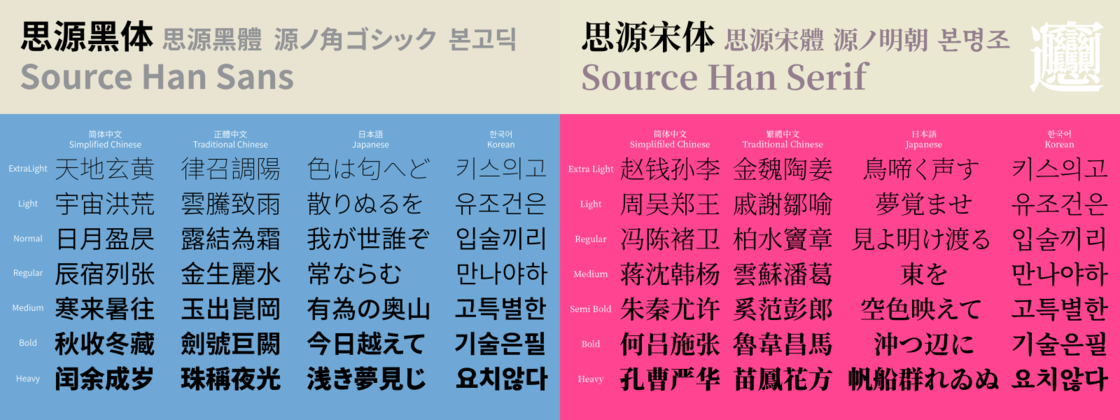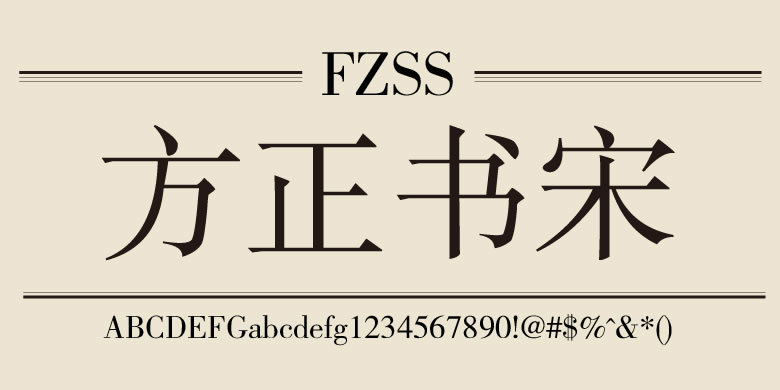
字体使用个人参考指南
文字作为我们交流的主要载体,手机、电脑、文书合同等各个方面。字体的侵权跟大多数版权内容一样,它的判定为两种:
1、商用
2、非商用
但是我们对字体版权的意识,往往不如其他内容版权那么关心,比如图片、影视、商标等等。因为文字过于常见,所以不小心就是一踩一个坑。
相比普通群体,更应该注意的是那些电商、小型公司、中小型公司以及大部分的创业群体。电商产品的宣传封面所使用的字体,很多时候为了节省成本,不会聘请专业美工,而那些接单的新手相对意识比较薄弱或者自己制作,就比较容易导致侵权。
给大家分享一个电商海报字体的案例,看下图。
这位从事电商行业的朋友,使用了未经方正授权的 “ 微软雅黑 ” 。
在图中也可以清楚看出,一旦侵权,那作为侵权方就尤为被动,一点话语权都没有。即便你有什么任何理由,也掩盖不了未经授权的事实。而在公司以及创业者方面,更多的是合同内容所使用的字体。这也可能是下文中的电商大站会自建或外购字体为其所用的一个最重要的原因吧。
在这里还要说明一点,电脑等等自带的字体不代表你有使用权,那是字体方授权给电脑系统使用,而不是给你商用的。拟定合同或者相关协议的时候,使用电脑自带文体正常不过的事情,但也要区分字体。
再看一个相关例子:
2019年,成都某公司的实习生,在拟定合同以及在宣传海报上使用了“微软雅黑”。并且这份宣传单被印刷了5000万张,发放到了全国各地。最后这家公司被索赔2860万,裁掉了8位主管和42位员工,公司一度濒临倒闭。这是多么痛的领悟。
这些都是真实事件,在网上动动手指都可以查到。而且你只要在网上搜索相关关键字,会发现这种案例比比皆是。
2011年,方正也因为字体侵权起诉飘柔。
2016年,某电商平台店主集体收到了侵权的律师函。
所以不管是大商家还是小商家、大公司还是小公司,对于字体的使用要保持一个严谨的态度,别一失足成千古恨。字虽小,但麻烦很大。
除了那些被我们熟知的宋体、黑体之外,还进行了系列梳理。
一、方正4款:方正黑体、方正书宋、方正仿宋、方正楷体。
二、思源2款:思源宋体、思源黑体。
三、王漢宗自由字型48款,内容太多,以图代字。
四、文泉驿字体4款:文泉驿等宽微米黑、文泉驿等宽正黑、 文泉驿微米黑、文泉驿正黑。
五、站酷字体4款:站酷酷黑体、站酷意大利体、站酷快乐体、站酷高端黑体
其中大多都是黑体、宋体的改变延伸,但不是代表所有带有 “ 黑 ” 或者 “ 宋 ” 字样的字体都是免费,微软雅黑就是例子。
字体有前缀或者参杂其他字样的,其实都应该引起注意,但也有解决办法,现在网络上有很多字体版权的查询网站,只要把你想用的字体输入,便可以查询是否为商用。
微软雅黑与北大方正
推动中文字体发展的居然是美国微软公司,为了让中文字体更好看,微软公司高价委托第三方字体设计公司开发了微软雅黑字体,每个汉字的造价成本在100美元左右,而我们有2万多个汉字。中文字体非常少,而优秀的中文字体更是凤毛麟角,我们常见的中文字体主要是宋体和黑体,其他很少见,因此,时间长了很容易出现审美疲劳,字体设计这一块做得最好的应该就是英文和日文了,其实我们是有能力开发优秀的中文字体的,但为什么就很少见呢?
2006年,微软的Windows Vista操作系统发布,为了让中文字体可以更清晰地显示,微软公司委托中国北大方正电子设计了一款全面支持ClearType技术的字体,就是现在人人熟知的微软雅黑字体,现在新的微软操作系统和程序默认的字体都是微软雅黑,另外还有网页上的字体基本上都是采用微软雅黑。
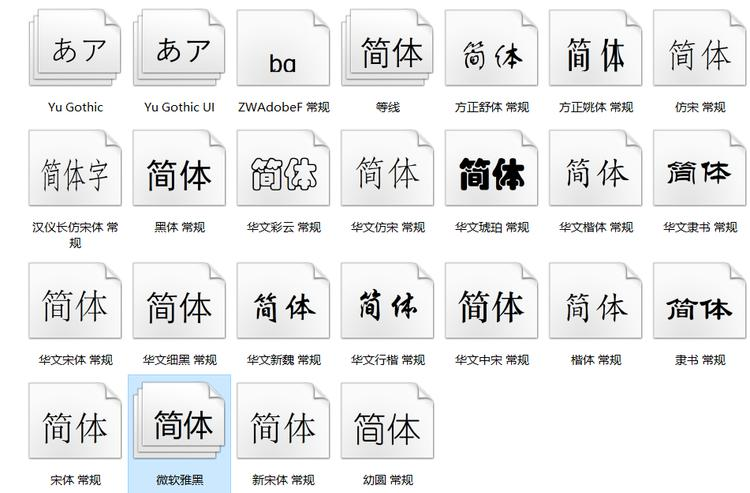
微软雅黑字体其实并不是完全免费的,微软雅黑的版权分为两个部分,一个是以个人使用为目的的Windows系统的内嵌使用、屏幕输出和打印,另一个是以商业发布为目的的微软雅黑版权,由北大方正保留,因此,用于商业目标的可能面临字体侵权,市面也有新闻报道过,上文也有引用,还是有不少公司使用了微软雅黑而被北大方正巨额索赔。也就是说:微软雅黑居然是北大方正开发的,一个字100美元卖给了美国微软公司。
中文字体设计,几十年了一直在原地踏步,其实说到底还是利益问题,国外有很多设计师就喜欢免费分享自己的作品,而国内设计师还没有这么高的境界。虽然字体设计还有一定差距,但这不是实力的问题,而是我们愿不愿意分享的问题,相信以后会有越来越多的优秀字体出现。
注意:没有醒目提示的,都要斟酌,不排除某些人就是靠此种手段谋利的可能,商用或者免费可能都会写在附文里,字小还多,很多朋友都不会认真阅读。如果真的喜欢一些需要付费的字体,就破点小财消大灾吧。说完上面的商用字体,下面就开始使用友好的字体介绍之旅吧。
字体侵权一说
本节摘自于张宇铭先生的总结。字体是受法律保护的,大家在使用时不能存有侥幸心理,来看看字体侵权问题案例。
影视作品侵权案例
2012 年的《九层妖塔》,仅使用了未授权字体中的 7 个字,就被索赔 51 万元。
电商广告侵权案例
电商也是字体侵权的重灾区,网络广告、海报、宣传语、商品包装、宣传视频、企业网站等。
如何界定一个字体的版权是否属于侵权?
所谓版权是专属知识产权,如果是大众的、通行的字体的使用不涉及版权争议,比如宋体,楷体,颜体……如果是自创体,不是大众使用与通用的,并在其中承赋了创造含量,或根据通用字体而编缉出版的字贴、字模等,并申报了相应的保护则具有了版权,如果被他人盗用则会涉及版权纠纷。
根据《中华人民共和国著作权法》的规定,作品在以下一些情况可以不经授权也不需要付费即可使用。为个人学习、研究或者欣赏;在介绍、评论中适当引用;为学校课堂教学或者科学研究;新闻报道;国家机关为执行公务合理范围内使用;公益陈列、保存、表演;转换成少数民族语文和盲文。对于字体内容,个人普通使用以及公益使用都应该采取自动获得授权方式。只要以合法手段取得已经发表的字体应用于以上领域,不需要获得授权,也不需要付费。
商业使用,不管是新设计字体还是作为文化遗产传承下来的宋体、仿宋、楷体、黑体等字体,都需要获得授权。新设计字体采取何种授权方式由著作权人决定。而宋体、仿宋体、楷体、黑体等传统字体作为全民族共有的非物质文化遗产,则应由国家相关机构代为管理。从理论上讲,如果取得收益应该返回给权利所有人,也可以变通为开放式授权,全民免费使用。但这仅应针对中国人,如外国企业作为商业使用,则需要取得正式授权。
字体产品的版权保护期。字体产品的版权保护也需要设置期限,应针对传统字体与新字体分别设置:传统字体按照《非物质文化遗产法》实行永久版权。新字体则适用《著作权法》和《计算机软件保护条例》,保护期为 50 年,期满转为公共资源,以鼓励不断创新。
依据《中华人民共和国著作权法》第三条,著作权包括文学、艺术和自然科学、社会科学、工程技术等版权,字体属于计算机字体库内容,平时在使用某系统时已经包含了其计算机字体库。
界定一个字体的版权:
1.确定字体是否收费,可通过拨打字体厂商电话,网络查询等。
2.确定是否用于商用,所有字体如果用于个人作品展示、参加各类非商业性比赛等非商业活动,字体厂商不追究版权问题。
3.确定是否变形,文字变形是否超过 50%,上述 50% 是法律法规界定,十分模糊,通常设计中字体变形或者造字,请注意变化尽量最大化。
商业使用的界定:商业使用包括以直接营利或者间接营利为目的,将字体作为视觉设计要素,进行复制、发行、展览、放映、信息网络传播、广播等使用字体的行为,比如,在企业宣传、广告设计、产品包装中使用。同时,设计者或产品开发者也不可以自行将「字体」嵌入其他 APP 或应用程序。另外,收费字体在未购买版权的情况下用于商业用途,且变形较少或无变形,即涉及侵权。
日常办公字体侵权案例分析
案例 1:
初始设定:字体,微软雅黑;软件名称,微软 office。
场景设定:因工作需要,需要把有微软雅黑字体的文稿,转化为 PDF、印刷物(海报、易拉宝、banner)、图片。
案例分析:
通过《著作权法》相关规定,使用字体需要获得字体所属方授权,此案例中,微软 office 软件都已取得方正公司字体授权,所以当查看的载体为微软 office 软件时,不涉及字体侵权。但PDF、印刷物、图片等都未经方正公司字体版权授权,所以当查看的载体为未经字体版权授权过时,已经涉及到字体侵权。
案例 2
初始设定:字体,微软雅黑。
场景设定:因产品需要,客户希望在 windows 的客户端查看网站都能够和设计稿保持一致用微软雅黑。项目组给了两种前端解决方案:
1).在 css 样式文件中:引用字体样式为微软雅黑。
2).在网站样式文件中,打包微软雅黑字体,客户打开网站会预加载微软雅黑字体。
请问两种解决方案应该用哪一个?
案例分析:
应使用第一种方案,因为第一种方案,我们只是设定了如果载体有安装微软雅黑的字体的客户端,那网站显示字体,这个字体授权的控制单位在客户端那里。如果用第二种方案,我们预置了,不管任何客户端都加载微软雅黑字体,除非客户已经购买了微软雅黑所属的方正公司授权商用,否则即判定为字体侵权。
案例 3
初始设定:字体,有版权的字体。
场景设定:因为客户需要,需要用到有版权的字体,设计师提出了版权问题,客户提出说是否可以少许改一下形,不变整个字体的感觉?
案例分析:
不可以,文字判断是否归版权方所有,必须超过 50% 的变形才视为其他字体。
从 3 个案例分析中,我们得出的结论为:
1).字体使用者在未经版权授权的情况下不可以自行将「字体」嵌入其他 APP 或应用程序。
2).收费字体在未购买版权的情况下用于商业用途,且变形较少或无变形,即涉及侵权。
避免字体版权侵权
1.识别字体是否有侵权
字体是我们工作中非常常用的东西,无论你是使用 Office 全家桶来完成文档,还是使用 Adobe 软件来制作设计稿,字体你是一定用的上的。判断字体是什么字体,才能够知道字体的版权方属于哪家企业,也才能够了解字体针对商用的授权情况是否需要收费还是免费。以下是 4 个字体识别平台推荐。
在介绍前先说明一点:在国内一些神秘网站(包括求字体网)可以找到中文字体,但是希望大家仅用于识别。因为大多数字体都是有版权限制的,如果在不知道版权要求的情况下随意下载,将会收到律师函等一系列的法律措施。
求字体网
字客网
字客网相对于前者来说,就要「干净」很多,视觉上用起来比较舒服,同样的也提供了关键词搜索和图片搜索两种方式。与此同时,字客网还支持进行实时的文本预览,在上方文本框输入你需要的文本内容并选择相关选项即可。其搜索内容比较丰富,除了可以搜索字体以外,还能了解到字体设计师、字体公司以及字体咨询等内容。在字体的详情页面,用户还可以浏览到该字体的详细参数。再次强调,在不知道版权要求的情况下,请勿随意下载。
选择合适的字体
无论你选择那个字体,你都有可能在每天中花费数小时面对它,所以请确保它在审美和哲学层面上与你产生共鸣。选择正确的开源字体是确保你拥有最佳生产环境的一个重要部分。这些字体都是很棒的选择,每个都具有让它脱颖而出的功能强大的特性。